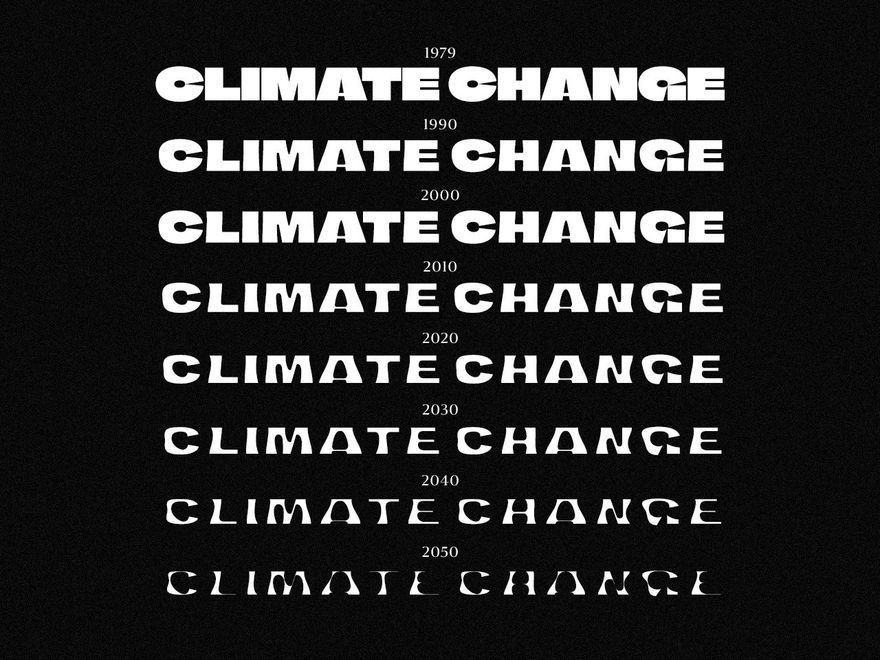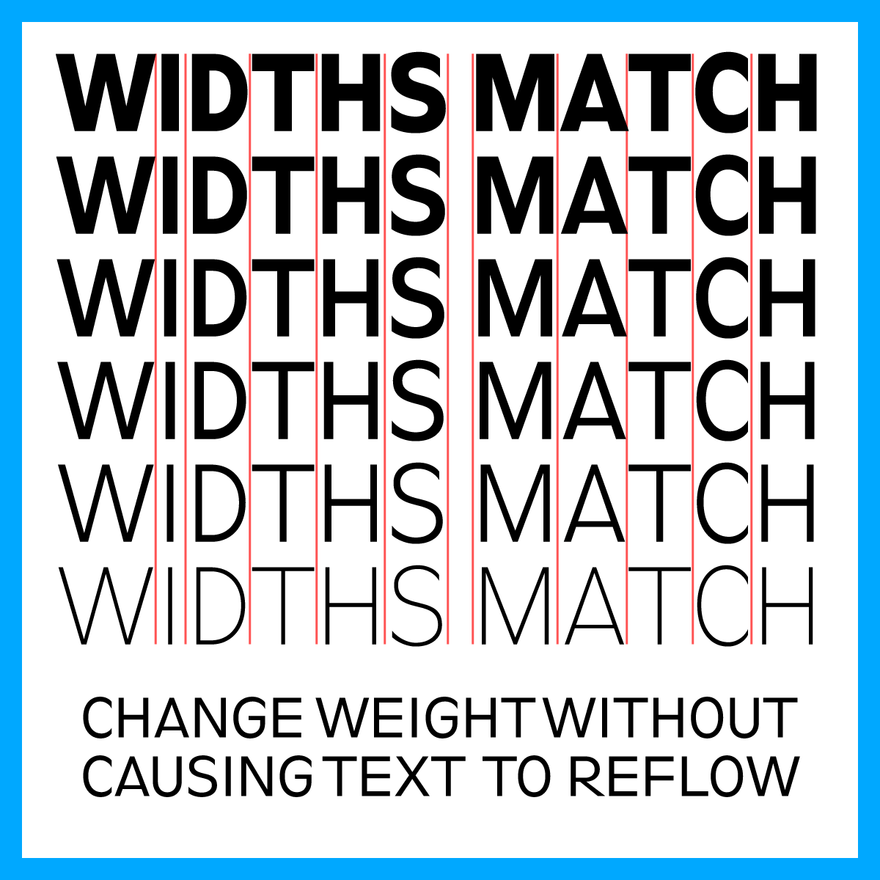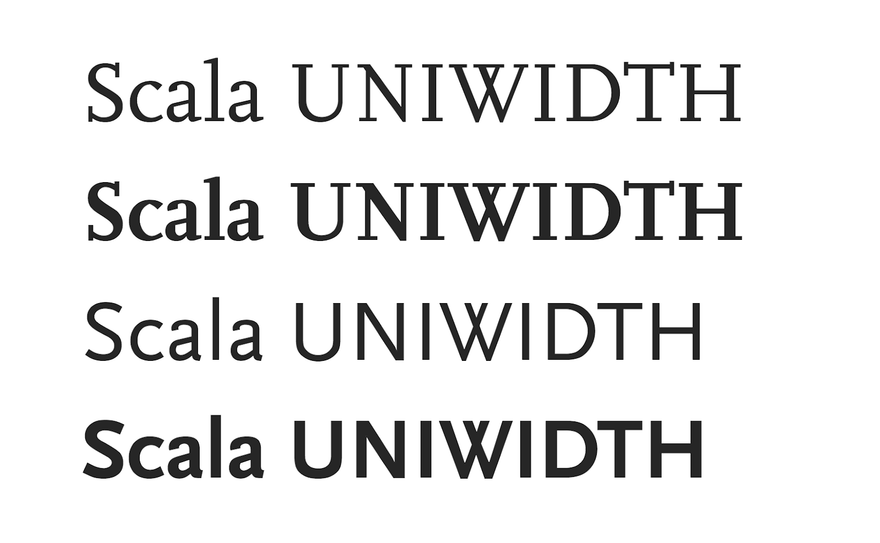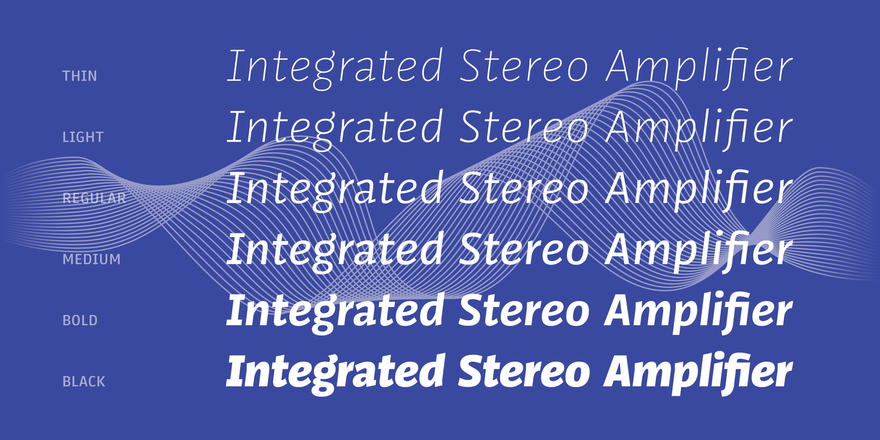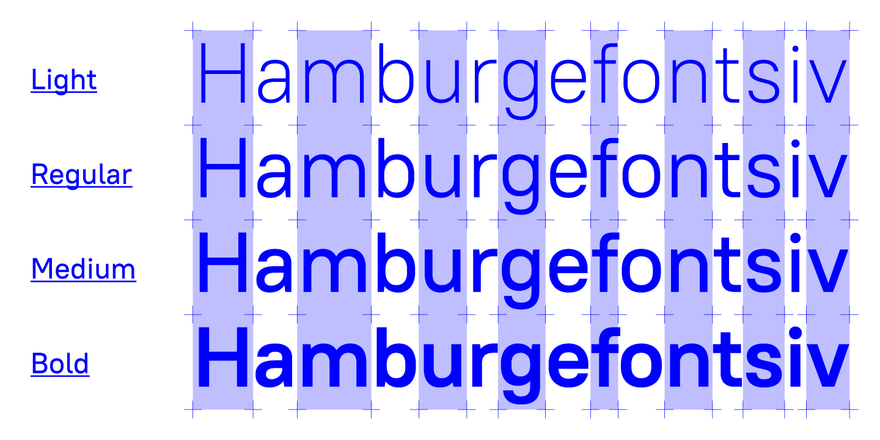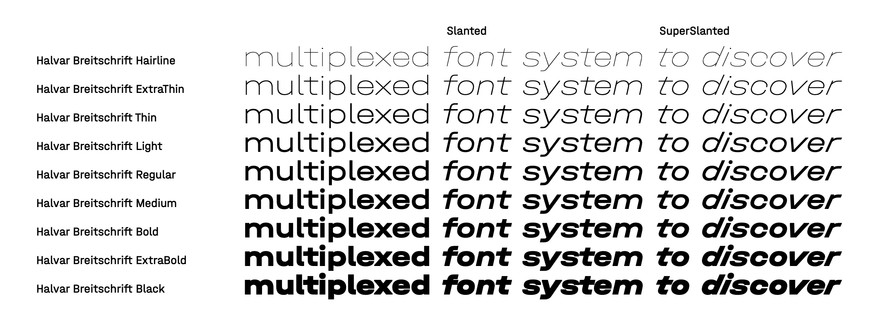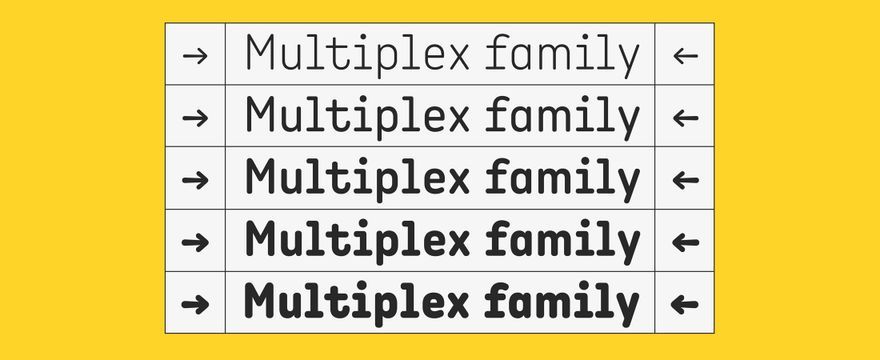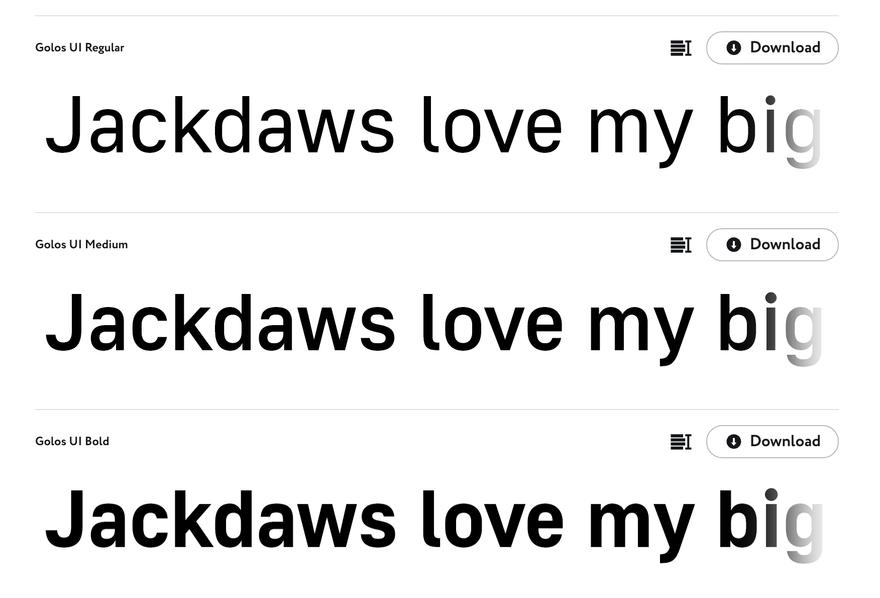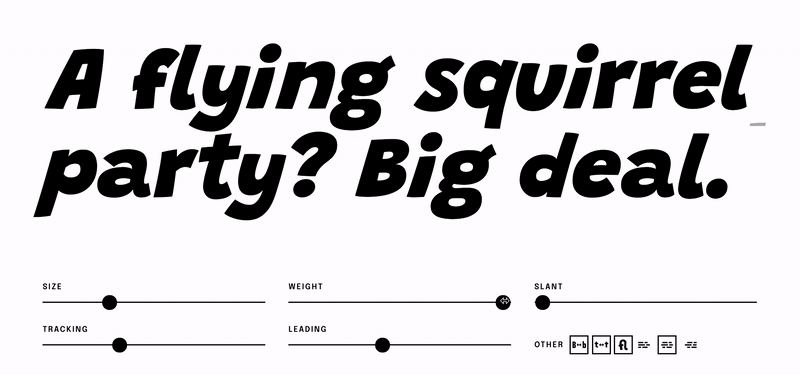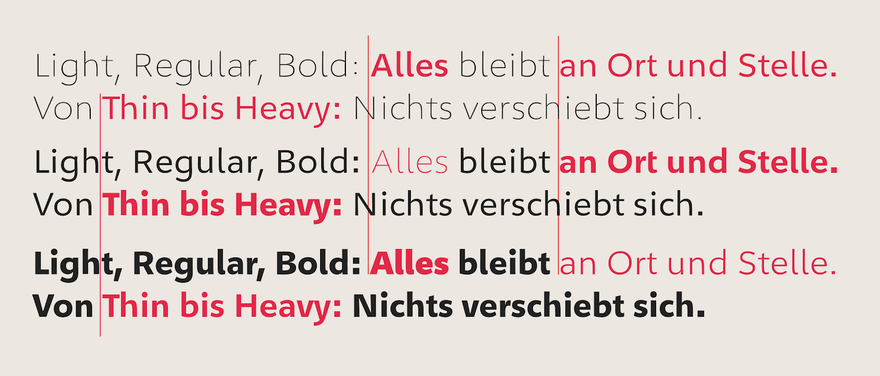
Пропорциональные (Uniwidth) шрифты имеют большой потенциал для использования в интерактивных интерфейсах. Это краткая подборка ряда доступных вариантов шрифтов.
Как веб / интерфейс / визуальный дизайнер, я много работаю с состояниями меток (selected, unselected, active, inactive, available, out of stock). Учитывая, что вы никогда не должны использовать цвет в качестве единственной визуальной подсказки (всегда помните о доступности), я часто прибегаю к помощи веса текста. Однако, если вы когда-либо работали с точно спроектированными интерфейсами, то знаете, насколько неприятно видеть, как ваши кропотливо размещенные метки сдвигаются, когда вы меняете вес текста с обычного на полужирный.
Решение этой проблемы: пропорциональные («uniwidth») шрифты, иногда также называемые «equal-width», «duplexed» или «multiplexed». И нет, я не имею ввиду моноширинные шрифты.
Краткое пояснение: моноширинный шрифт, также называемый непропорциональным – это шрифт, буквы и символы которого занимают одинаковое количество горизонтального пространства (например, A в верхнем регистре такой же ширины, как w в нижнем регистре, или знак €). Моноширинные шрифты традиционно используются на пишущих машинках, а в наши дни – для ввода компьютерного кода.
В моноширинном шрифте, таком как IBM Plex Mono, каждая буква имеет одинаковую ширину
С другой стороны, пропорциональные (Uniwidth) гарнитуры представляют собой гарнитуры с пропорциональным интервалом, но каждый символ занимает одинаковое пространство при разном сокращении или толщине. На практике это означает, что независимо от того, какой вес вы установили для текста, он никогда не изменит его длину или не вызовет перекомпоновку.
Обычно буквы пропорциональных гарнитур имеют разную ширину и разный вес, но в пропорциональном шрифте с одинаковой шириной (uniwidth) разные веса занимают одинаковое пространство
Хотя эта функция позволяет создавать несколько креативных слоев в статическом наборе, она чрезвычайно ценна для дизайна интерфейса, где, как правило, все быстро идет наперекосяк с внесением небольших изменений. Например, изменение веса отдельного пункта меню при наведении курсора обычно приводит к беспорядочным подергиваниям всего меню, когда оно пытается приспособиться к изменению. Использование пропорционального шрифта решает эту проблему легко и без необходимости в дополнительном коде.
Используя пропорциональный шрифт, можно легко анимировать вес интерактивных текстовых элементов, не затрагивая окружающий макет
Учитывая также, что мы наблюдаем рост числа вариативных шрифтов, которые часто позволяют плавную интерполяцию между разными весами, пропорциональные шрифты, безусловно, чрезвычайно ценны для проектов интерактивного дизайна.
На данный момент существует не так много ресурсов о пропорциональных гарнитурах. Пока что я нашел два ресурса: список «Equal-width fonts» от Identifont и коллекцию 2015 года «Uniwidth typefaces» от Дэвида Судвикса. Оба ресурса содержат значительное количество различных вариантов.
Учитывая особые потребности интерфейса и веб-дизайна, а также распространение вариативных шрифтов в последние годы, я, тем не менее, ожидаю (и надеюсь) в ближайшем будущем увидеть гораздо больше пропорциональных шрифтов.
А поскольку никогда не бывает много вариантов шрифтов, вот еще несколько пропорциональных гарнитур, которые я недавно нашел. (Примечание: я не включаю в эту подборку моноширинные гарнитуры, поскольку они, как правило, однонаправленные, и их гораздо легче найти).
Recursive от Arrow Type
Recursive – это вариативный шрифт, созданный для «максимальной универсальности, контроля и производительности». Recursive доступен в пропорциональной и моно версии, и обе можно дополнительно контролировать по четырем осям: Weight, Casual, Slant и Cursive. Casual повторяет мягкие и изогнутые мазки кисти и добавляет немного веселья к серьезному шрифту. Recursive поддерживает широкий спектр языков, использующих латинский алфавит, включая вьетнамский. Он также содержит расширенный набор валют, символов, дробей и стрелок.
PT Root UI от Paratype
PT Root UI – это современный, серьезный шрифт без засечек, который бывает четырех типов (Light, Regular, Medium, Bold). PT Root UI специально спроектирован для чтения с экрана, интерфейсов и веб-сайтов. Он имеет широкую языковую поддержку, включая расширенную латиницу и кириллицу (включая азиатскую кириллицу), и содержит табличные цифры, знаки валюты, дроби и индексы, а также ряд стрелок и альтернативных форм.
Golos UI от Paratype
Шрифт Golos UI, также от Paratype, имеет три веса (Regular, Medium, Bold), а также доступен как вариативный шрифт. Golos UI в целом похож на PT Root UI, но имеет немного суженные пропорции. Он обладает широкой языковой поддержкой, включая расширенную латиницу и кириллицу (в том числе азиатскую кириллицу), и содержит табличные цифры, знаки валюты, дроби и индексы, а также ряд стрелок и альтернативных форм.
Golos UI можно бесплатно загрузить по лицензии SIL Open Font License (OFL) на веб-сайте Paratype.
Источник: Paratype
Grandstander от Etcetera Type Company
www.etceteratype.co/grandstander
Grandstander – это игривый вариативный шрифт без засечек, вдохновленный детскими книгами, который «понравится людям всех возрастов». Буквы изогнуты и слегка вздуты, что придает ему комическую эстетику. Grandstander поставляется в статической версии с девятью весами (от Thin до Black) с соответствующим курсивом. Вариативная версия имеет две оси: Weight и Slant. Он поддерживает «широкий спектр языков, использующих латинский алфавит» и включает в себя табличные цифры, а также дроби, альтернативы и лигатуры.
Grandstander можно бесплатно загрузить на условиях OFL (Open Font License) в Google Fonts и Github.
Источник: ETC
Angus от Black Foundry
Angus – это современный шрифт без засечек с закругленными концами, который имеет четко выраженный моноширинный вид. У Angus пять весов (от Light до Extrabold) с соответствующим наклонным курсивом. Angus поддерживает набор латинских шрифтов и включает строчные (минускульные) и табличные цифры, дроби и индексы, лигатуры и стрелки.
Angus можно купить на сайте Black Foundry.
Источник: Black Foundry
Halvar и Halvar Stencil Complete от TypeMates
www.typemates.com/fonts/halvar-and-stencil-complete
Halvar – это массивная система шрифтов, насчитывающая в общей сложности 162 стиля. Halvar и Halvar Stencil имеют три значения ширины (Wide, Normal и Condensed), а также девять весов (от Hairline до Black) с двумя вариантами курсива (Slanted и SuperSlanted). Halvar с громоздкими пропорциями и сложными формами представляет собой прагматичный гротеск. Halvar поддерживает расширенный латинский, греческий и кириллический алфавиты и имеет табличные цифры, надстрочные индексы, дроби, а также альтернативные символы.
Halvar можно приобрести на сайте TypeMate. Также доступен предрелизный вариант вариативного шрифта.
Источник: TypeMates
Service Gothic от HEX
Service Gothic – это незавершенный вариативный шрифт, в настоящее время доступный только в верхнем регистре. Service Gothic включает 6 статических весов от Thin до Bold.
Первую версию Service Gothic можно купить на сайте Future Fonts.
Источник: Future Fonts
Urby и Urby Soft от TypeMates
Urby Collection призван «объединить поразительный характер с технической функциональностью». Urby и его закругленный аналог Urby Soft выпускаются в пяти вариантах веса (от Thin до Black). Их можно использовать как взаимозаменяемые, поскольку они одинаковы по ширине для всех весов в обоих семействах. Urby Collection поставляется с расширенной поддержкой латинского алфавита и включает в себя линейные и табличные цифры, надстрочные и подстрочные индексы, дроби, порядковые числа и широкий спектр полезных декоративных элементов и геометрических фигур.
Urby Collection можно приобрести на сайте TypeMates.
Источник: TypeMates
Geóso от Finaltype
finaltype.de/de/projekte/geoso
Geóso – это гуманистический шрифт без засечек с геометрическим оттенком. Этот шрифт доступен в девяти весах (от Thin до Heavy) с соответствующим курсивом и является универсальным для каждого стиля. Geóso поддерживает расширенный набор латинских шрифтов и имеет обширную и сложную систему цифр, надстрочных, подстрочных и дробных знаков. В качестве бонуса Geóso содержит неуловимую немецкую заглавную букву ß и забавный набор кастомных смайлов.
Geóso можно приобрести на сайте FrontSpring.
Источник: Finaltype
FF Kaytek family от FontFont
www.fontshop.com/superfamilies/ff-kaytek
FF Kaytek – это «свежий взгляд на канцелярские гарнитуры 90-х». Это обширное суперсемейство, состоящее из четырех стилей: Slab, Sans, Headline и Rounded. FF Kaytek Slab и Sans имеют шесть весов (от Thin до Black) плюс соответствующий курсив, в то время, как FF Kaytek Headline и Rounded имеют по семь весов (от Thin до ExtraBlack/Black). Headline and Rounded стили дополняют друг друга и имеют более компактный вид, чем Slab и Sans. FF Kaytek пропорциональный по весу и курсиву в каждом стиле.
Суперсемейство FF Kaytek поддерживает расширенный набор латинских шрифтов и имеет старые цифры, дроби, а также надстрочные и подстрочные индексы.
FF Kaytek доступен в FontShop и MyFonts.
Источник: MyFonts
Bahnschrift от Saja Typeworks
docs.microsoft.com/en-us/typography/font-list/bahnschrift
Bahnschrift – это оцифрованная версия шрифта DIN, известного по немецким дорожным знакам. Bahnschrift был первым вариативным шрифтом Microsoft, имеющим две оси: Weight и Width. Существует статическая версия, которая включает пять весов и три ширины. Bahnschrift поддерживает расширенную латиницу (включая вьетнамский), а также кириллицу и греческий алфавит.
Bahnschrift доступен как часть операционной системы Windows 10.
Источник: Microsoft
FF Scala family от FontFont
Семейство FF Scala – это классика печати. Спроектированный в 1991 году Мартином Майором, шрифт FF Scala с засечками в старом стиле был позже расширен версией без засечек, FF Scala Sans, основанной на общем скелете. Оба семейства имеют два веса (Regular и Bold) с соответствующим курсивом и двумя сокращенными стилями. Семейство FF Scala поддерживает расширенную латиницу и включает строчные и табличные цифры, надстрочный и подстрочный индекс, дроби, порядковые числа и фирменный набор декоративных стрелок.
Семейство FF Scala доступно для покупки на веб-сайте FontShop.
Источник: FontShop
Помимо обычно очень умеренных шрифтов для основного текста, есть также несколько доступных декоративных пропорциональных шрифтов:
Minérale от 205TF
Minérale – это вариативный шрифт с необычными основами, грани которых пересекаются. Minérale «довольно сдержанный в своих самых тонких версиях, [но] становится более декоративным в более тяжелых версиях». Статическая версия шрифта имеет пять вариантов веса (от Extralight до Black) и соответствующий курсив. Все они являются пропорциональными (включая версии с курсивом). Minérale поддерживает расширенный набор латинских шрифтов и включает пропорциональные фигурные цифры, пропорциональные строчные цифры, табличные цифры, ординалы, стилистические альтернативы и стрелки.
Minérale можно приобрести на сайте 205TF.
Источник: 205TF
Climate Crisis Font от Helsinki Sanomat
kampanjat.hs.fi/climatefont/index.html
Шрифт Climate Crisis Font – удивительный вариативный шрифт, который пытается пролить свет на изменения климата. Ось веса шрифта основана на данных National Snow and Ice Data Center и прогнозах, предоставленных IPCC. Самый жирный шрифт представляет минимальную протяженность арктического морского льда в 1979 году, а самый легкий представляет собой прогноз на 2050 год.
Шрифт Climate Crisis Font поддерживает основной набор латинских шрифтов и имеет ограниченный набор надстрочных знаков и дробей.
Climate Crisis Font можно бесплатно загрузить в соответствии с лицензией SIL Open Font License (OFL) от Helsigin Sanomat.
Символы шрифта Climate Crisis Font неизменно широкие, но кажется, что они «тают» при выборе более легкого веса. Источник: Helsingin Sanomat
Handjet от Rosetta Type
Handjet – экспериментальный трехкоординатный шрифт на основе сетки. Система шрифтов Handjet содержит 23 элементарных формы (например, квадраты, клевер и сердечки), размер которых можно изменять, создавая различный вес шрифта. Кроме того, можно использовать группы из меньших элементов 2x2 вместо одного элемента. Как и следовало ожидать от Rosetta Type, Handjet поддерживает широкий спектр языков: арабский, армянский, кириллицу, греческий, иврит и расширенную латынь. Он также включает дроби и достаточно забавные маленькие украшения.
Handjet можно купить за 0 евро на веб-сайте Rosetta Type.
Источник: Rosetta Type
Вывод
Возможность изменять вес и стиль текстов, не влияя на занимаемое ими пространство – это функция, которая имеет большое значение для интерфейсов. Это не только избавит дизайнеров и разработчиков от головной боли, но и откроет новые возможности для создания доступного дизайна. Поскольку выпускается все больше и больше вариативных шрифтов, я рад добавить больше пропорциональных шрифтов в свой набор инструментов проектирования интерфейса. А вы?
Для дальнейшего чтения по теме
Если вы пропустили ссылку выше, есть намного больше пропорциональных шрифтов, которые я не упомянул в этой статье, но которые собраны на этих замечательных ресурсах:
Список «Equal-width fonts» от Identifont
«Uniwidth typefaces» от Дэвида Судвикса